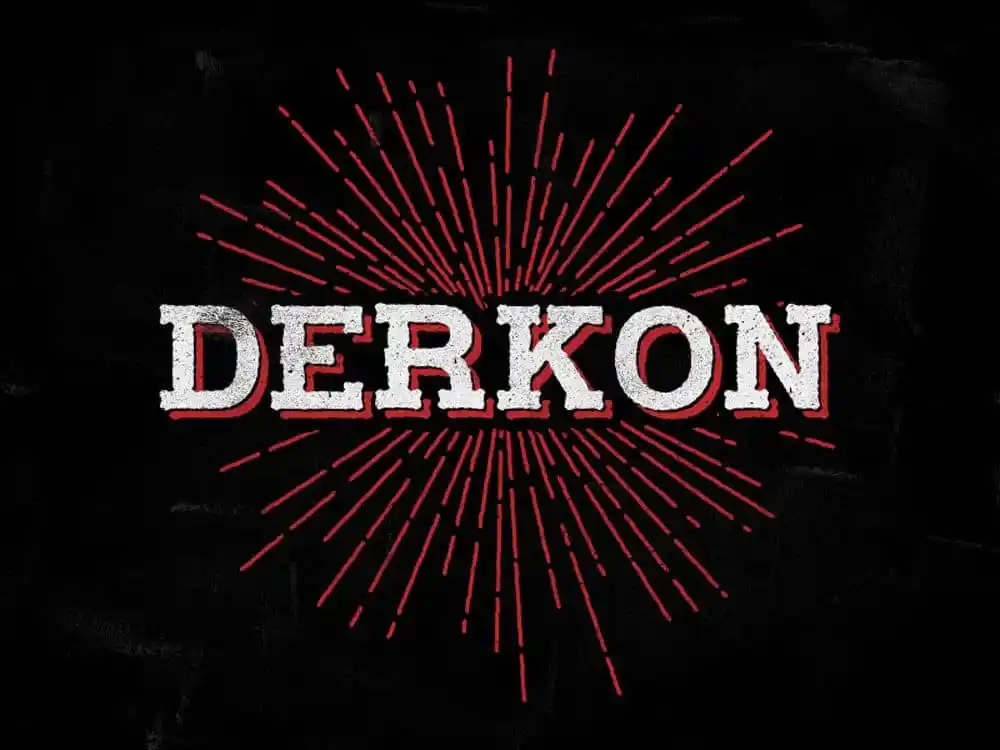
Derkon Typeface
Introduzimos Derkon! Esta fonte de tipo foi criada pelo designer eightonesix.net e incorpora características vintage, retro e incrivelmente únicas. Com diferentes pesos, Derkon é perfeito para layouts de revistas, cartões de convite, cabeçalhos ou até mesmo trabalhos de arte em grande escala. Suas linhas leves e elegantes criam um visual moderno que se adapta a uma variedade de ambientes gráficos, tornando-a uma escolha interessante para designers visuais. Derkon é o tipo de fonte que vai destacar seu trabalho de design e certamente encantará os amantes do bom estilo vintage.